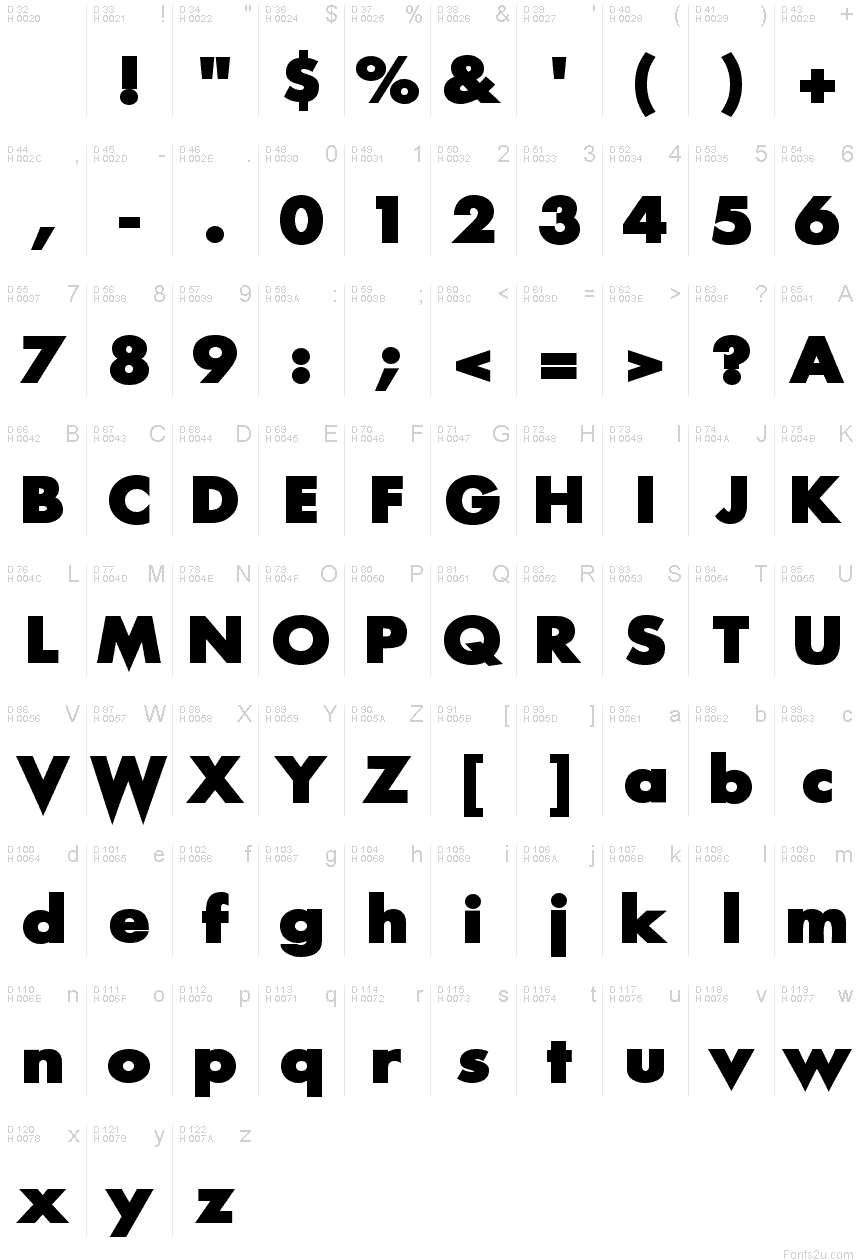
Scream Alternative von Samuel Park ist eine kostenlose Horror-Sans-Serif, die auf der visuellen Identität der Scream-Filme basiert. Die Buchstaben sind wuchtig, schwer und eng gesetzt, wobei weiche Kurven auf scharfe Schnitte und flache Verbindungen treffen – das verleiht dem Schriftbild eine maskenhafte, filmische Spannung statt des üblichen neutralen Sans-Charakters.
Es eignet sich perfekt für Filmplakate, Halloween-Flyer, Streaming-Thumbnails, Coverlines und Titelkarten, bei denen ein paar Worte diesen Slasher-Vibe der späten 90er brauchen. Als Free-Font passt es zudem hervorragend zu Zines, Fan-Art, Merchandise-Mockups und kurzem Branding, besonders wenn man abgerundete Formen mit einem harten, fast schon abgehackten Rhythmus sucht.
Based on the Scream films logo. Samuel Park -99